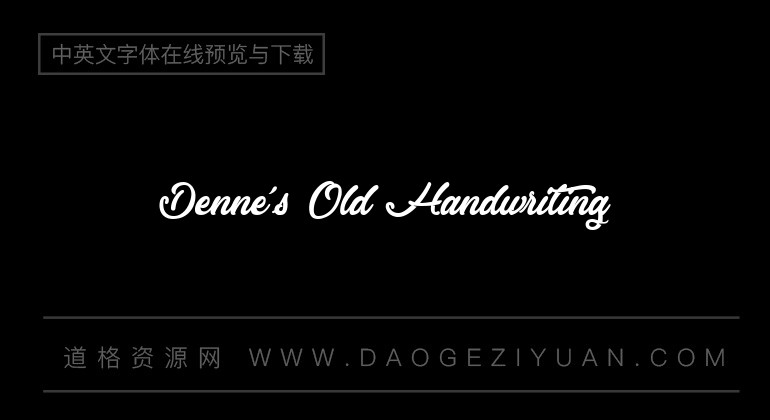
Denne's Old Handwriting 字体是一种仿古体字体,其风格仿照了16世纪和17世纪时期的手写字体。该字体特点是具有复杂的连笔和装饰性的元素,适合用于模拟历史文献、手写信件、书籍封面等需要传统风格的设计项目。 Denne's Old Handwriting 字体是基于英语和拉丁字母表设计的,对于其他语言而言,其可用性可能有所限制。内容介绍
Denne's Old Handwriting是一款非常不错的手写艺术字体,具有很好的视觉感,适合于文化类的宣传设计、商业类品牌的广告和产品包装设计以及个性化文字排版等较多场景。